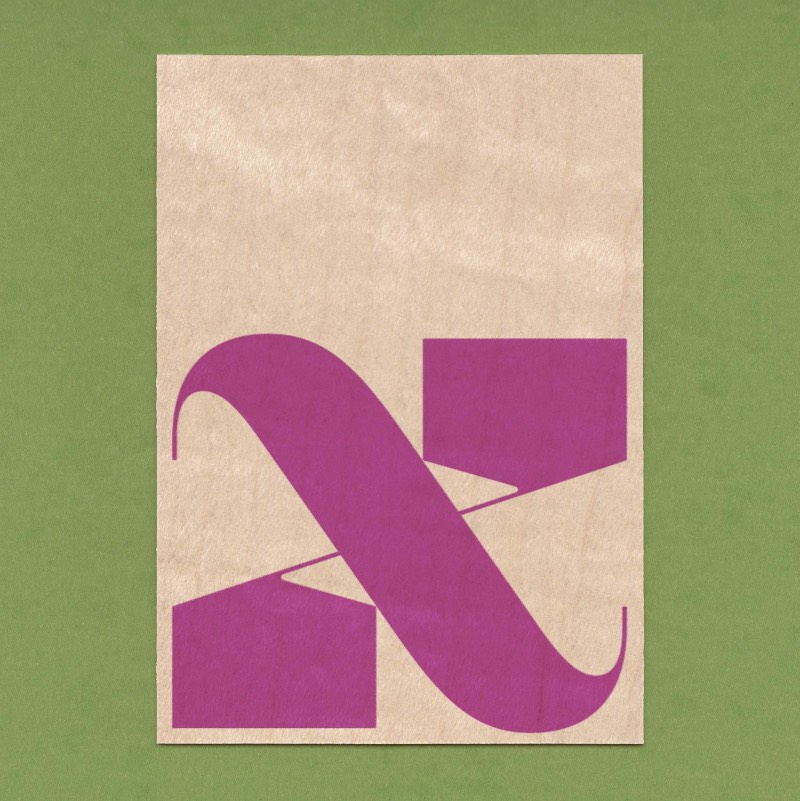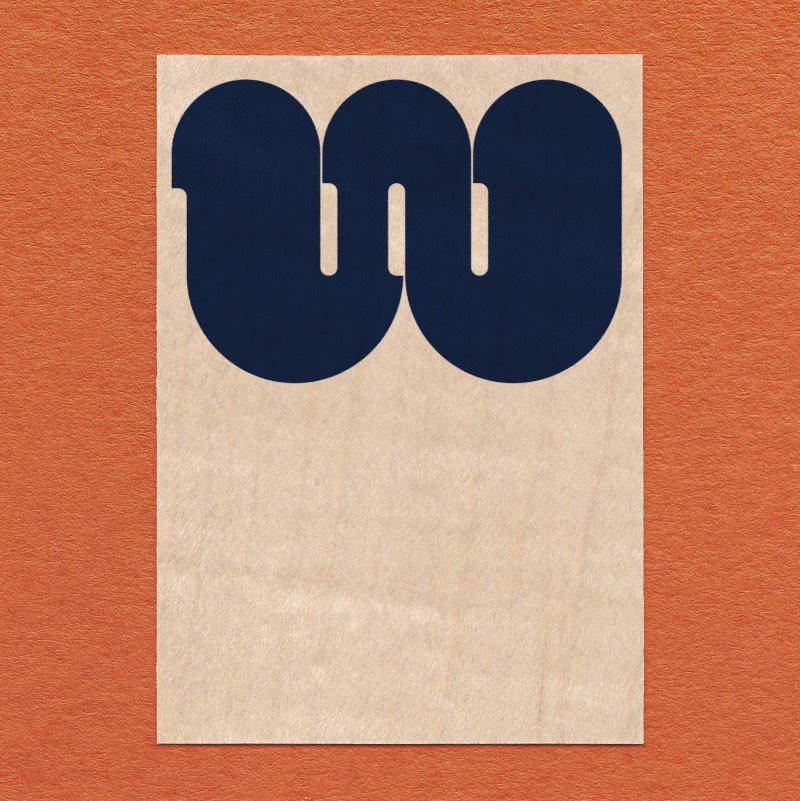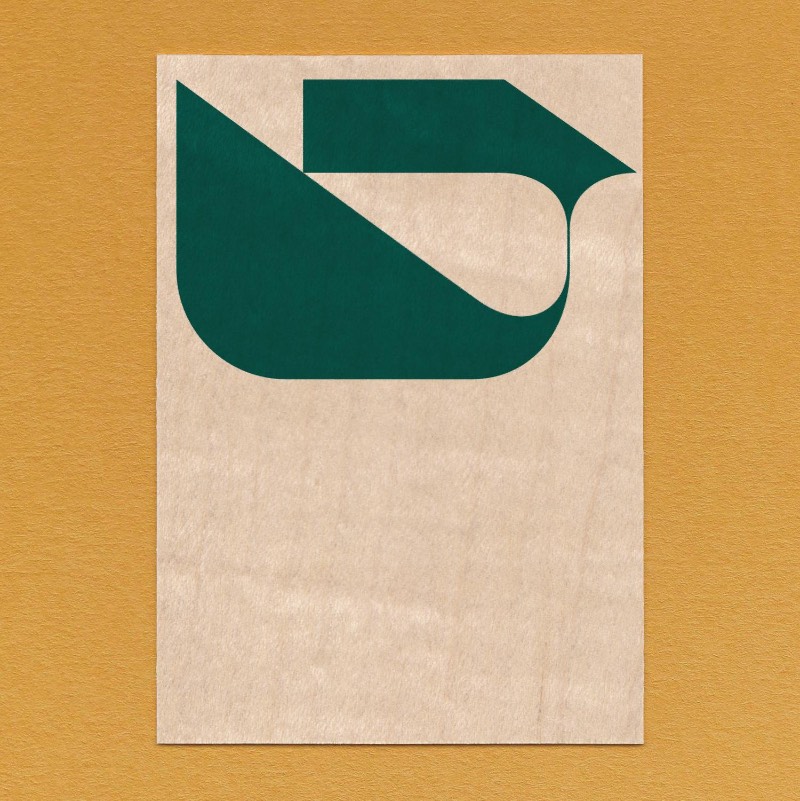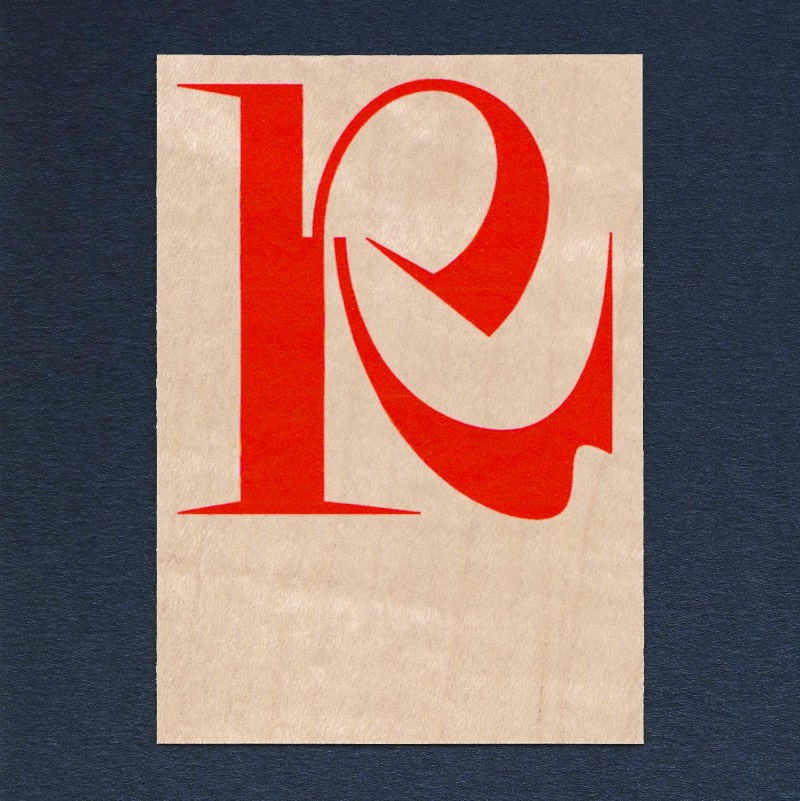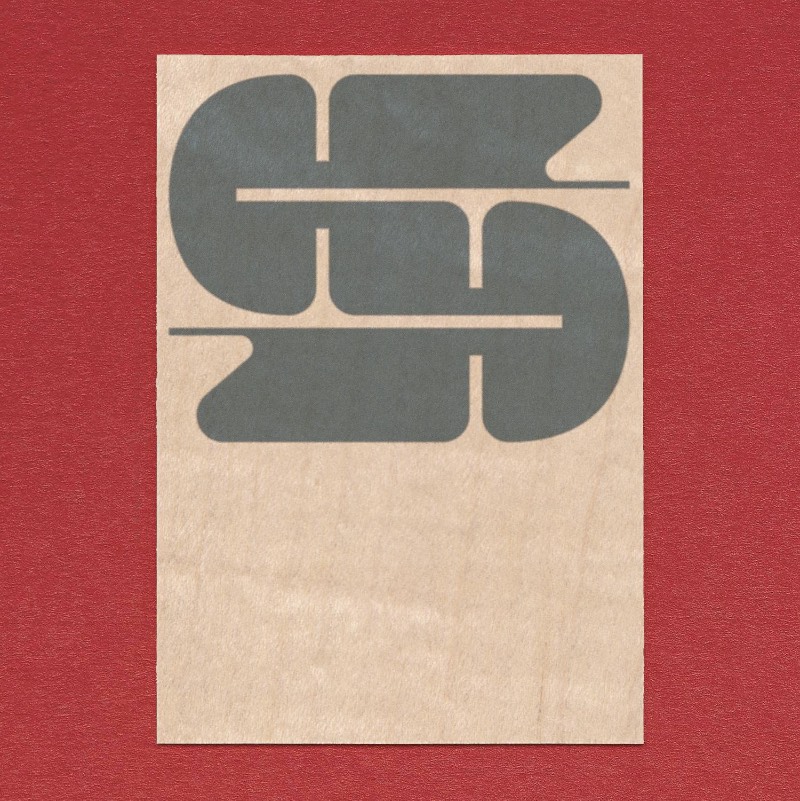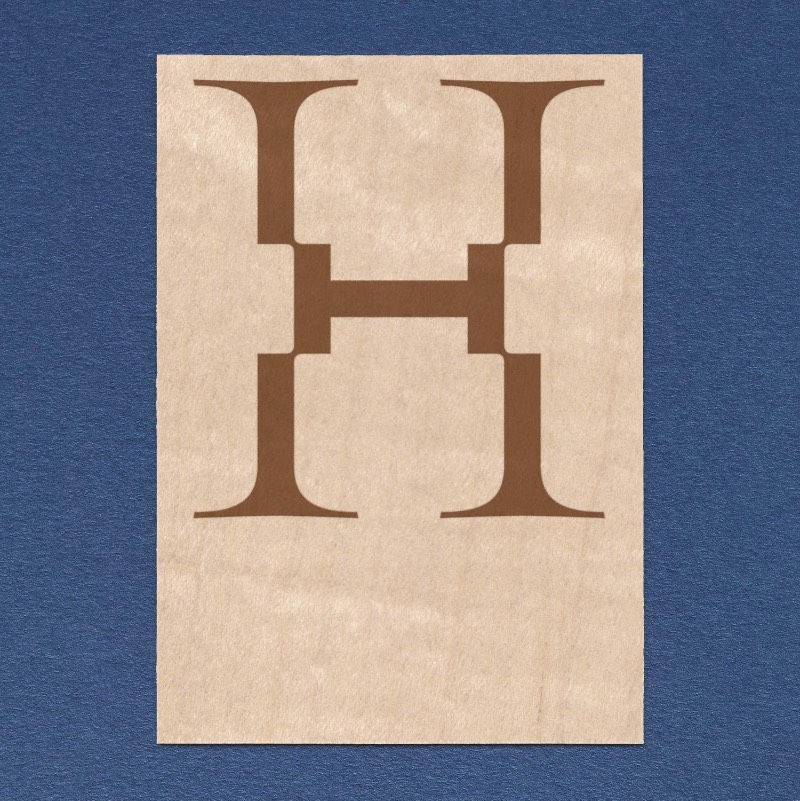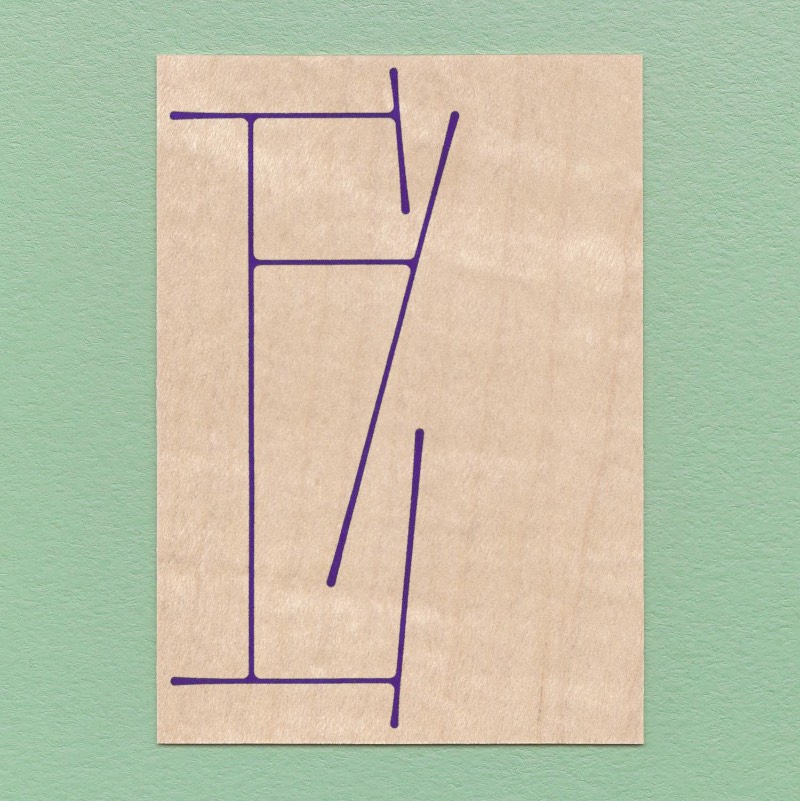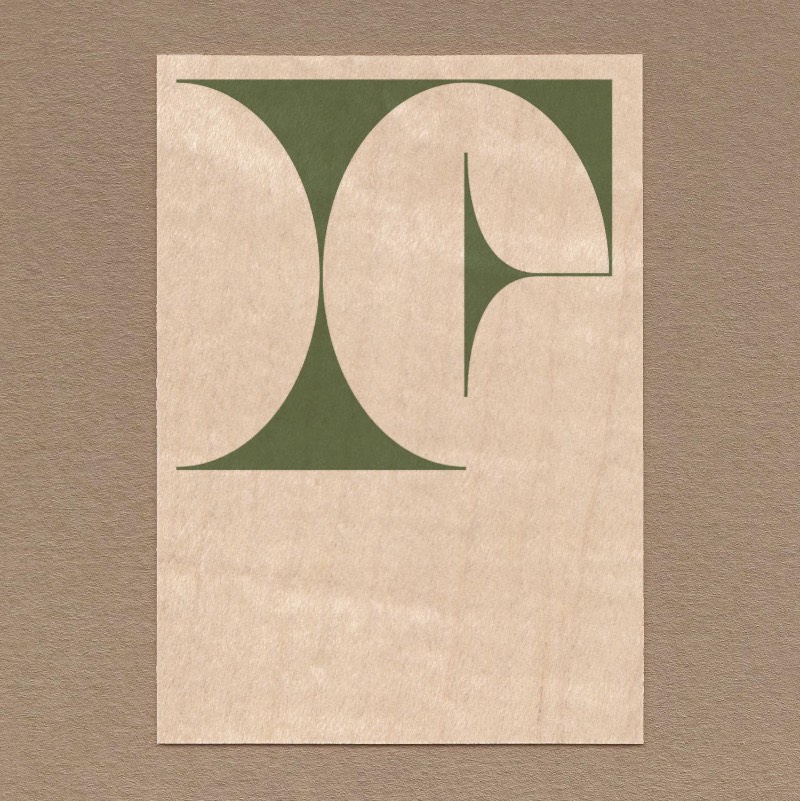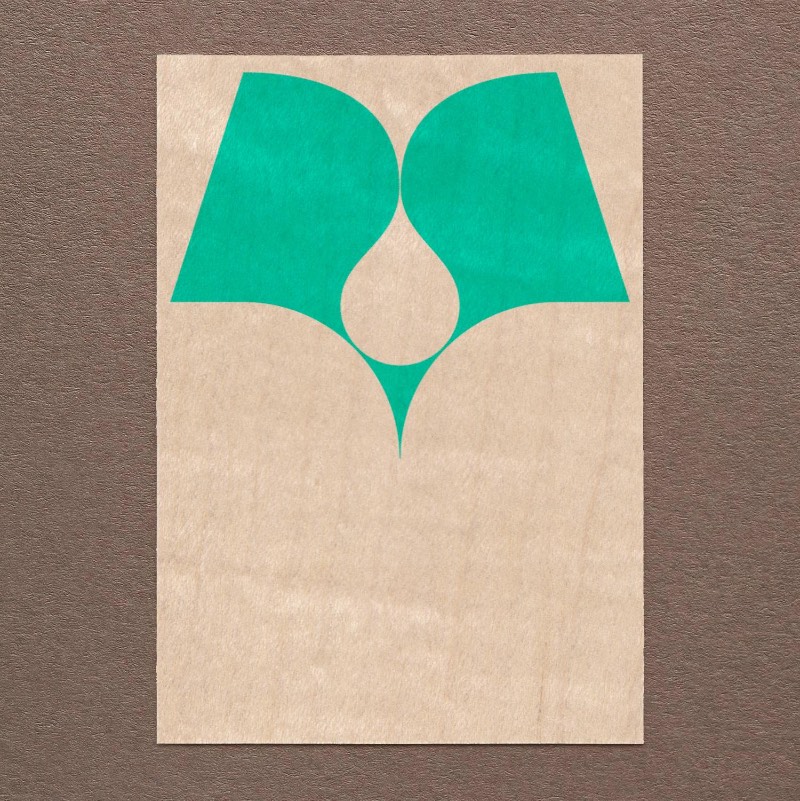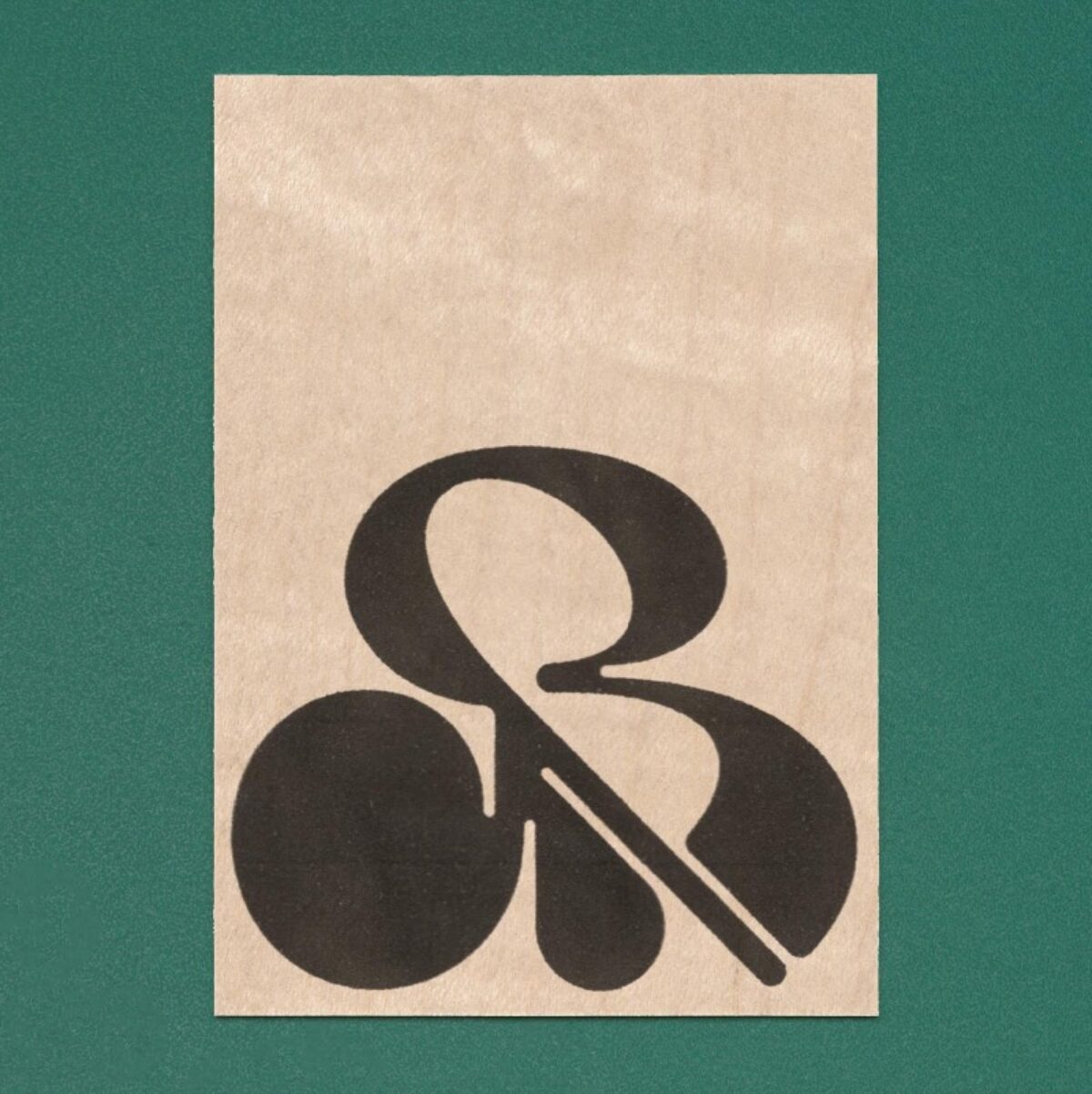
Os Glifos Aleatórios de Kiros Chu
Depois de um longo dia de trabalho como freelancer em Toronto, o designer gráfico Kiros Chu resolve parar com seus trabalhos oficiais e começa a fazer seus projetos pessoais. Ele faz isso com a ideia de exercitar alguns músculos criativos diferentes e eu entendo isso muito bem já que faço a mesma coisa no meu dia a dia aqui em Berlim.
Entre todos os projetos experimentais e aleatórios, como ele os descreve em seu portfólio, o que mais chamou a minha atenção foi o que ele resolveu chamar de Random Glyphs e que eu traduzi diretamente como glifos aleatórios. Aqui ele experimenta com a tipografia e cria letras com um visual bem diferente onde a experimentação é a única direção viável.
Esse projeto parece ter surgido como um subproduto do que ele fez para seus 36 dias de tipografia. Parece que o designer estava explorando o visual de uma letra e começou a seguir para uma direção mais ilustrativa. Depois de alguns momentos, ele entendeu que o que ele estava fazendo já não combinava mais com o que ele tinha e que o inesperado ali merecia se tornar outra coisa. Foi assim que o Random Glyphs virou um projeto por si só.
A partir dessa decisão de transformar o Random Glyphs em algo especial, ele começou a desenhar diferentes letras, tudo sem limites definidos e explorando um lado realmente experimental. Dessa forma, ele se tornou o designer, o cliente e o público final em simultâneo, e, também, esse lado do projeto serviu muito como um aprendizado para ele.
Kiros Chu acredita que o Random Glyphs fez com que ele passasse a enxergar a tipografia e as letras de uma forma diferente. Algo que ele acredita que vai levar seus projetos visuais para um nível diferente de sofisticação. Além disso, ele ainda tem vários glifos que não foram finalizados e que merecem ser melhor explorados num futuro próximo. Quem sabe eles não se tornam parte de um projeto para clientes?